Стимпанк
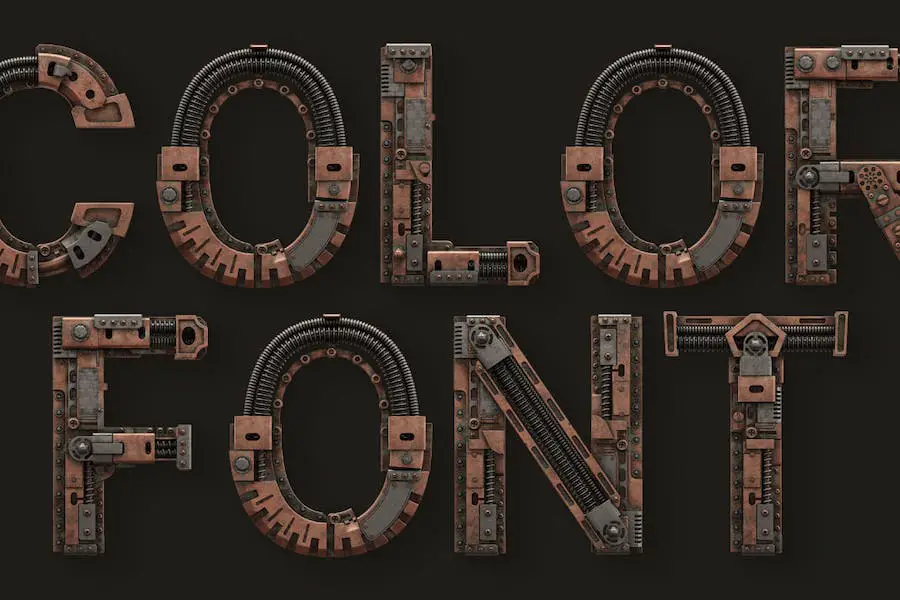
Steampunk — это уникальный и инновационный шрифт, который придаст вашим проектам 3D-эффект. Этот цветной или SVG-шрифт OpenType, совместимый с Photoshop CC 2017+, Illustrator CC 2018 и некоторыми приложениями Mac, идеально подходит для графических дизайнеров, желающих улучшить свои проекты.
Одной из выдающихся особенностей Steampunk является возможность создавать текстовую область по всему окну. Однако важно убедиться, что все буквы находятся в этой области, чтобы полностью оценить шрифт.
Если вы заметили какие-либо части букв за пределами отведенного места, просто отрегулируйте интервал, чтобы буквы отображались правильно.
Цвет
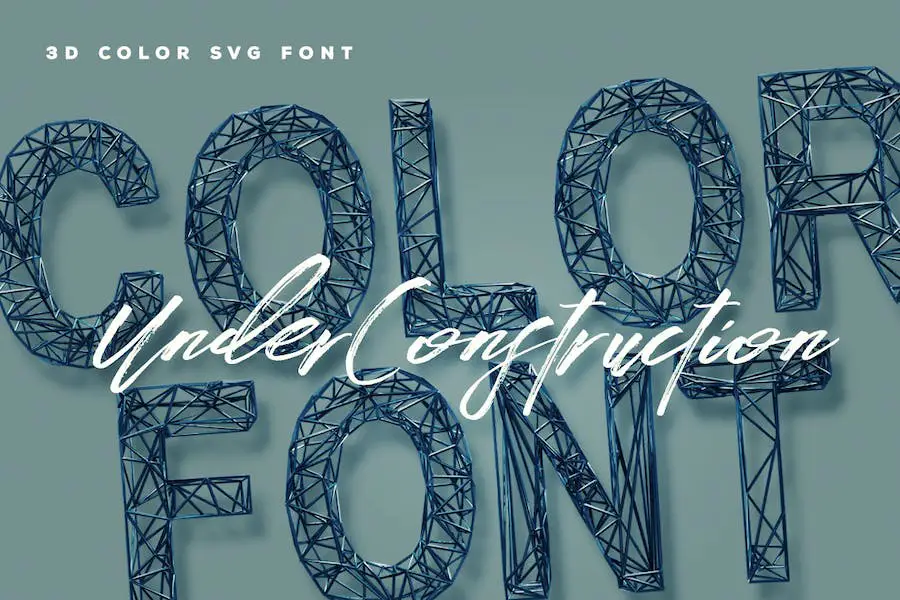
Color — это универсальный и привлекательный 3D-шрифт, который поднимет ваши дизайнерские проекты на новый уровень. Этот уникальный шрифт идеально подходит для графических дизайнеров, которые хотят добавить глубину и объем своим творениям. С помощью Color вы можете создавать потрясающие визуальные эффекты, которые очаруют вашу аудиторию.
Универсальность Color выходит за рамки его дизайнерских возможностей. Этот шрифт также подходит для широкого спектра проектов и отраслей.
Независимо от того, разрабатываете ли вы дизайн для Google или Adobe или даже создаете татуировку, Color — надежный выбор. В этом шрифте есть все: от металлических 3D-шрифтов до каллиграфии и граффити.
Промышленная коробка
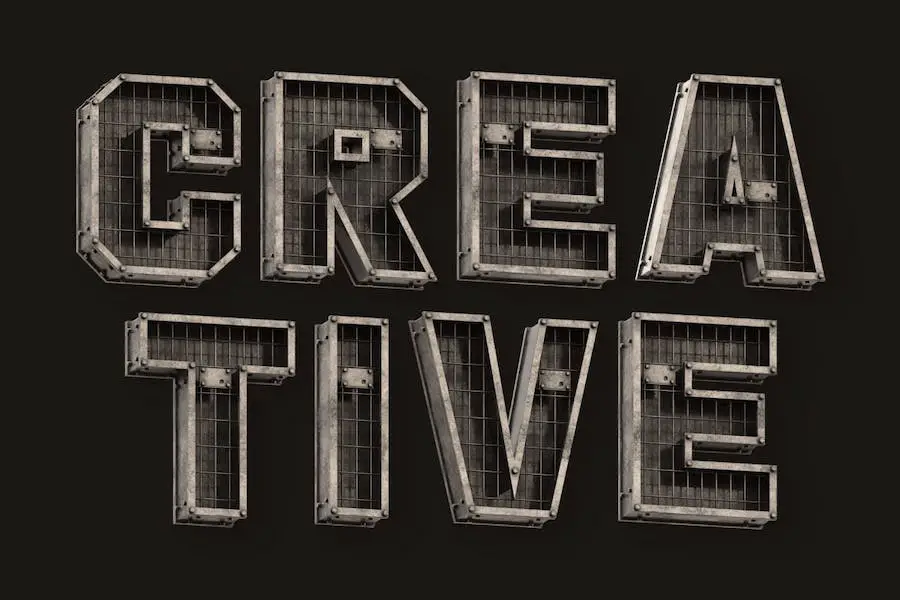
Industrial Box — универсальный шрифт, который добавит изысканности вашим проектам графического дизайна. Это цветной или SVG-шрифт OpenType, который без проблем работает с Photoshop CC 2017+, Illustrator CC 2018 и некоторыми приложениями Mac.
С Industrial Box вы можете улучшить свои проекты и без особых усилий создавать потрясающие визуальные эффекты. Независимо от того, работаете ли вы над логотипами, плакатами или графикой для социальных сетей, этот шрифт улучшит общую эстетику вашего проекта и выделит его из толпы.
Его совместимость с передовым программным обеспечением для проектирования гарантирует, что вы сможете раскрыть свой творческий потенциал без каких-либо ограничений. Так зачем же соглашаться на обычные шрифты, если вы можете улучшить свой дизайн с помощью Industrial Box? Попробуйте и посмотрите, как это повлияет на ваши проекты!
Хромированные трубы
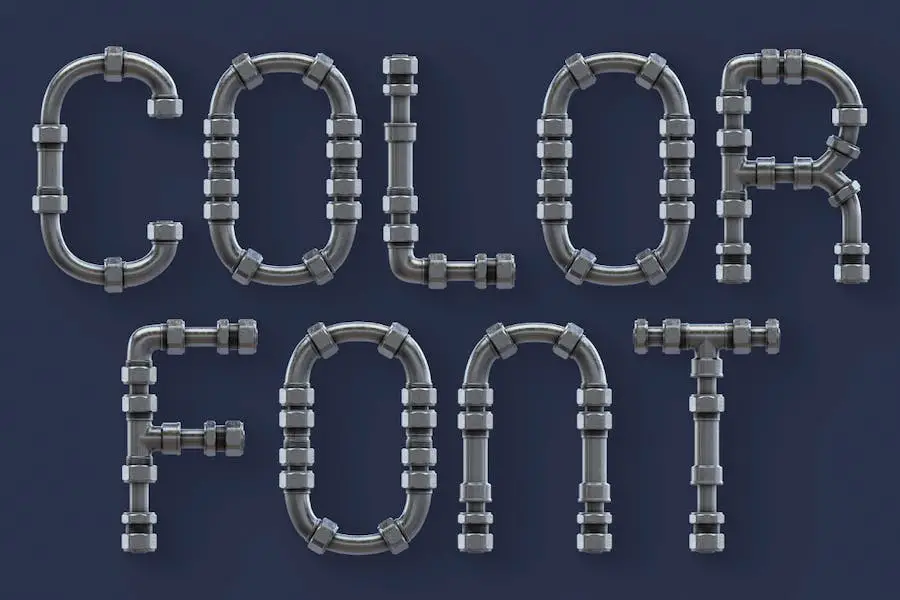
Chromium Pipes — это цветной или SVG-шрифт OpenType, разработанный специально для использования в Photoshop CC 2017+, Illustrator CC 2018 и некоторых приложениях Mac. Этот шрифт придает уникальный трехмерный вид вашим проектам графического дизайна, позволяя создавать привлекательные и визуально привлекательные проекты.
Благодаря совместимости с этим высококачественным программным обеспечением для проектирования Chromium Pipes открывает мир возможностей для графических дизайнеров, желающих поднять свои проекты на новый уровень.
Независимо от того, работаете ли вы над плакатом, логотипом или любым другим дизайнерским проектом, этот шрифт наверняка усилит общее визуальное воздействие.
Медные трубы 2
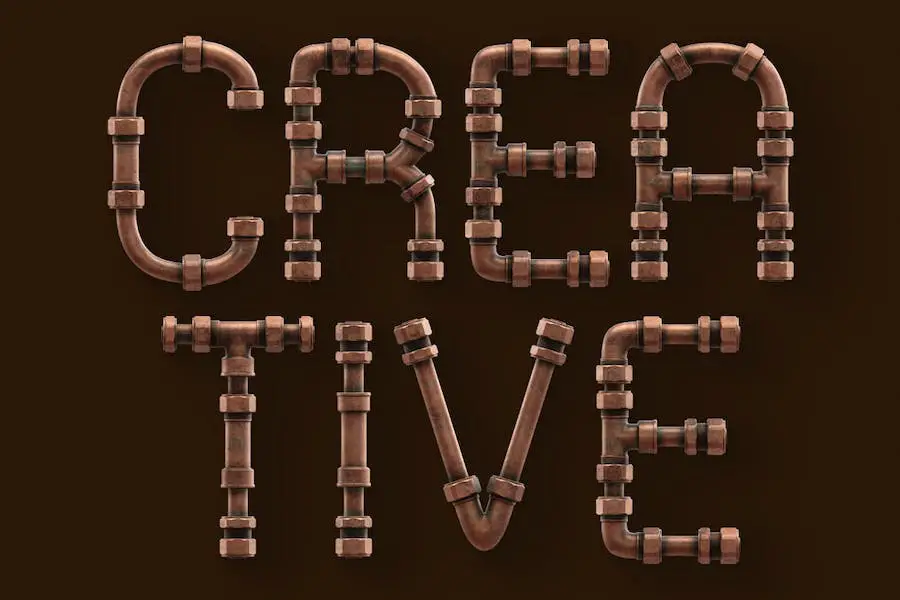
Copper Pipes 2 — универсальный и привлекательный шрифт, который идеально подходит графическим дизайнерам, желающим улучшить свои проекты. Этот цветной или SVG-шрифт OpenType специально разработан для бесперебойной работы с Photoshop CC 2017+, Illustrator CC 2018 и некоторыми приложениями Mac.